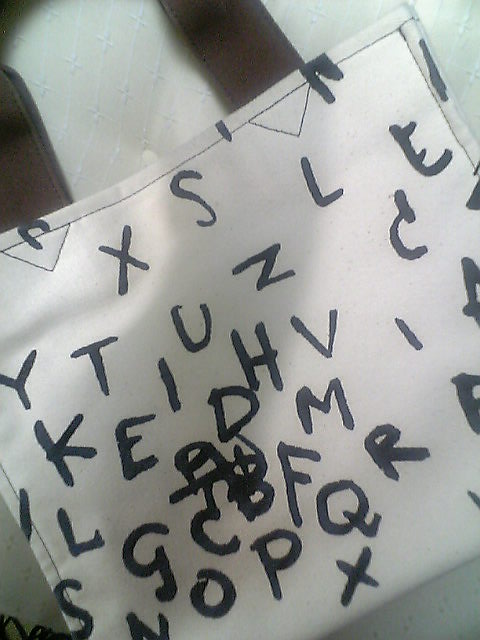
パウル・クレー 絵画のたくらみ
日本人はクレー?!私もですが、mojitor-sさんはクレー協会会員だし、mojitor-hさんはベルンのクレーセンターに行ってたしな〜。
皆、色にひかれ、形に見入り、技巧に興味をもち、何が描いてあるんだろう、何を使って描いているだろうと魅入る。やさしく穏やかな絵でありながら、これ何?さて何?
この本は、そんな知りたかったことがわかりやすく対話形式で解説されていてとてもおもしろい、納得、お得。
中でもやはり一番うれしかったのは、「第2章 なぜ文字なのか?」
Calligraphyという本の中にクレーの作品が載っていて、モノラインのキャピタルのネガティブ、ポジティブスペースを色を入れているもので、画家もこんなことしてたんだ〜すてき!と思ってから久しいですが、クレーは1914年に意味ある単語やテキストを画面に取り込んだ文字絵を書きはじめたそうで、その中の中国詩のドイツ語訳の作品についての解説が載っています。
他にもポストカードを持っている「歌姫ローザ・ジルバーの声の織物」、芸術新潮に掲載されていた、これはいったい何文字だろう?の「証書」も解説されてうれしい。
そして、なにより、お〜(*゚∀゚)っと思ったのは、去年の3月のクレー展で購入したmojitor-hさんがブログでも紹介していたキャンパス地バック、私も愛用しておりますが、その作品!!!!!!!
「詩のはじまり」の解説があり、バックにますます愛着〜。
バックは、作品の一部なので、ただ文字が散らばって入るように見えるだけですが、作品には、単語と数字が描かれていて、1から5の番号順に読むと「このようにしてそれはひそかにはじまる」というセンテンスになるそうです。